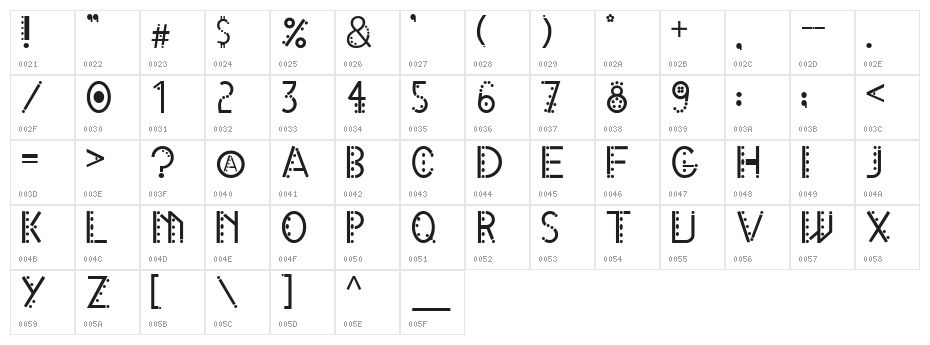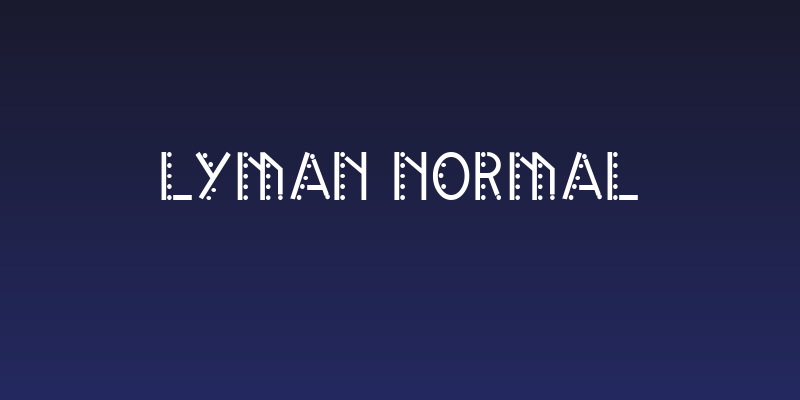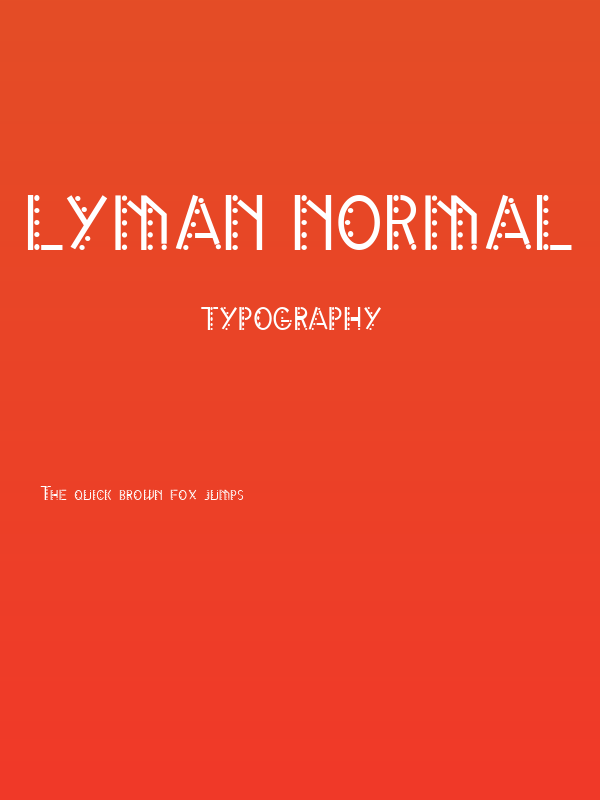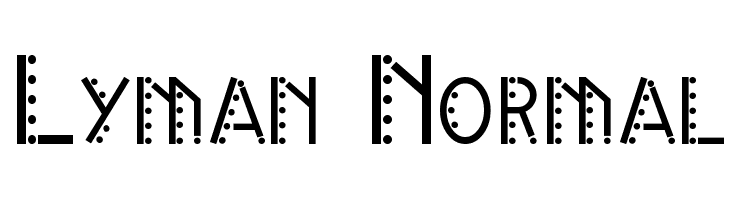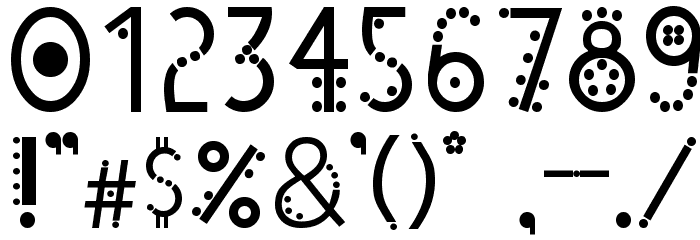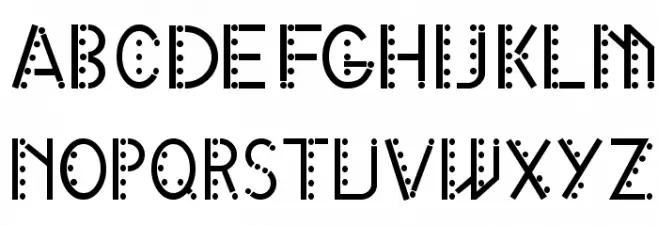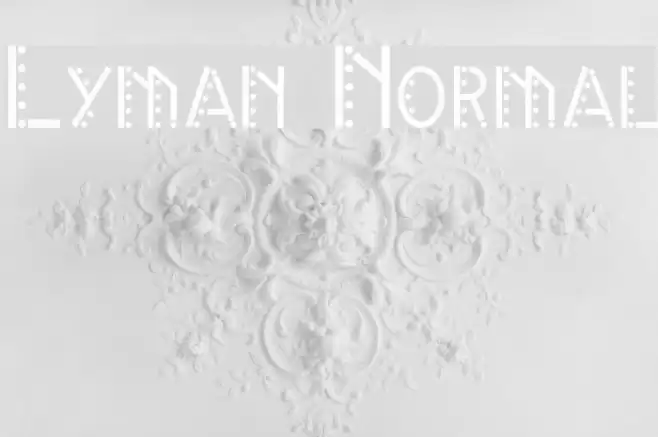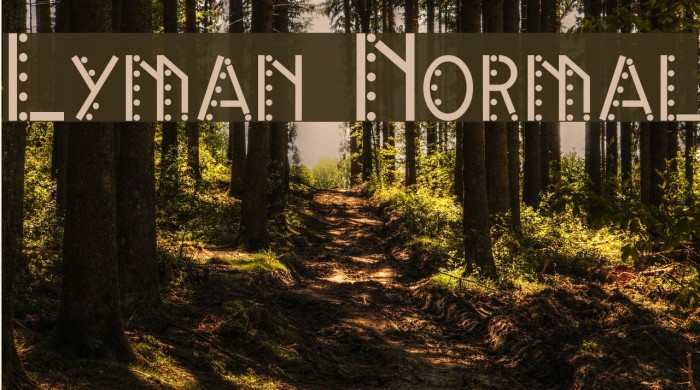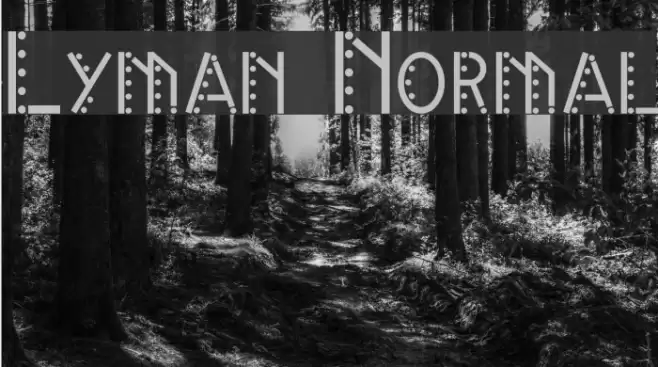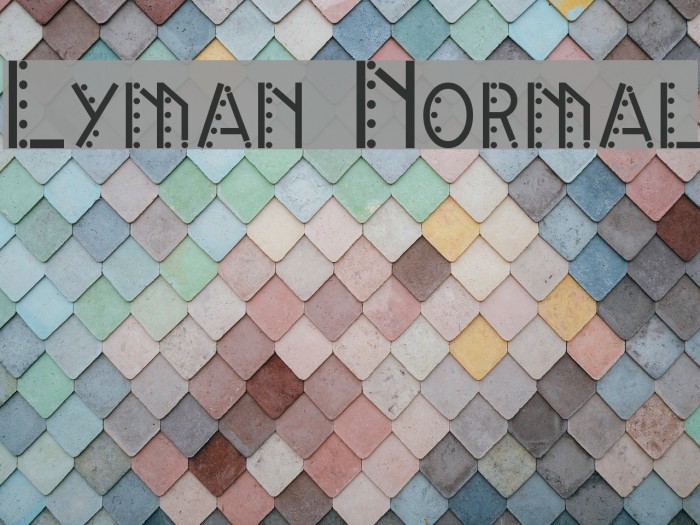
Lyman Normal Font
| Proyectos propuestos | Ideal for creative projects such as posters, invitations, and branding materials where a unique and eye-catching typeface is desired. |